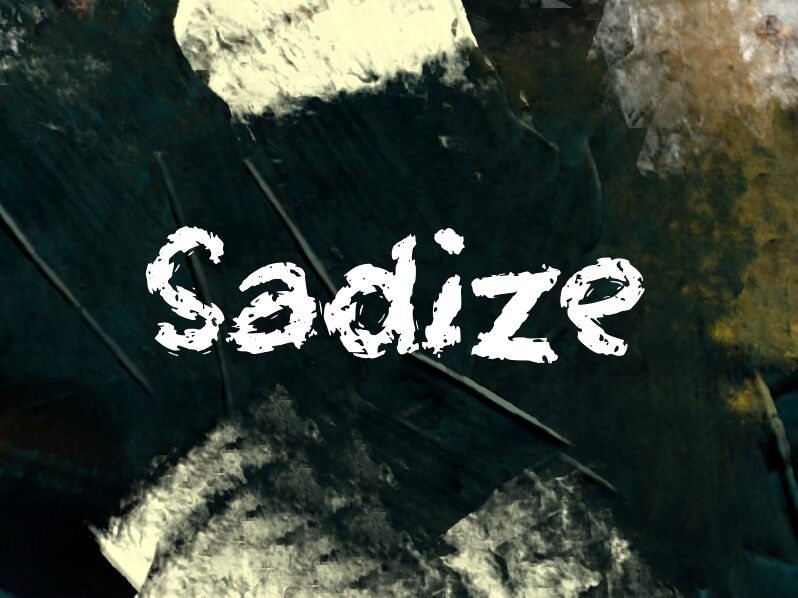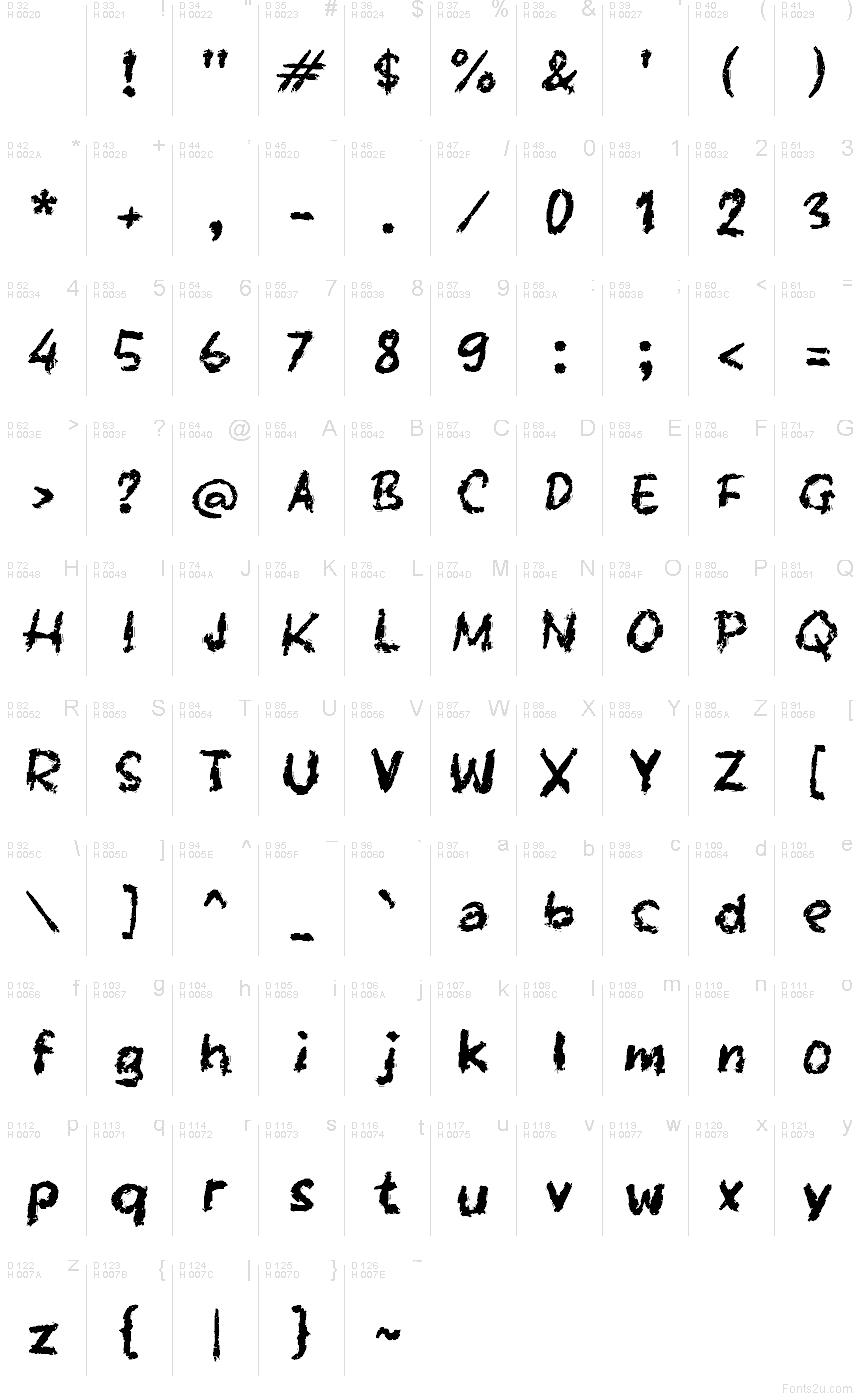
Sadize von Wep ist eine kostenlose Trash-Brush-Schrift mit einem schroffen, wilden Rhythmus, die sich anfühlt, als wäre sie von Hand hingeschmiert statt akkurat gezeichnet. Die Buchstabenränder wirken aufgerissen, mit groben Trockenpinsel-Aussetzern und stumpfen, fleckigen Enden, die der Schrift einen rauen Street-Vibe verleihen.
Sie passt perfekt zu Postern, Mixtape- oder Album-Artworks, Skate-Grafiken, Zine-Covern und Horror-Titeln, bei denen eine saubere Schrift zu glatt wirken würde. Als kostenlose Schrift eignet sich Sadize auch hervorragend für kurze Schlagzeilen, Logo-Skizzen und raue redaktionelle Akzente, da die unebene Textur die Stimmung ganz von allein erzeugt.
Sadize